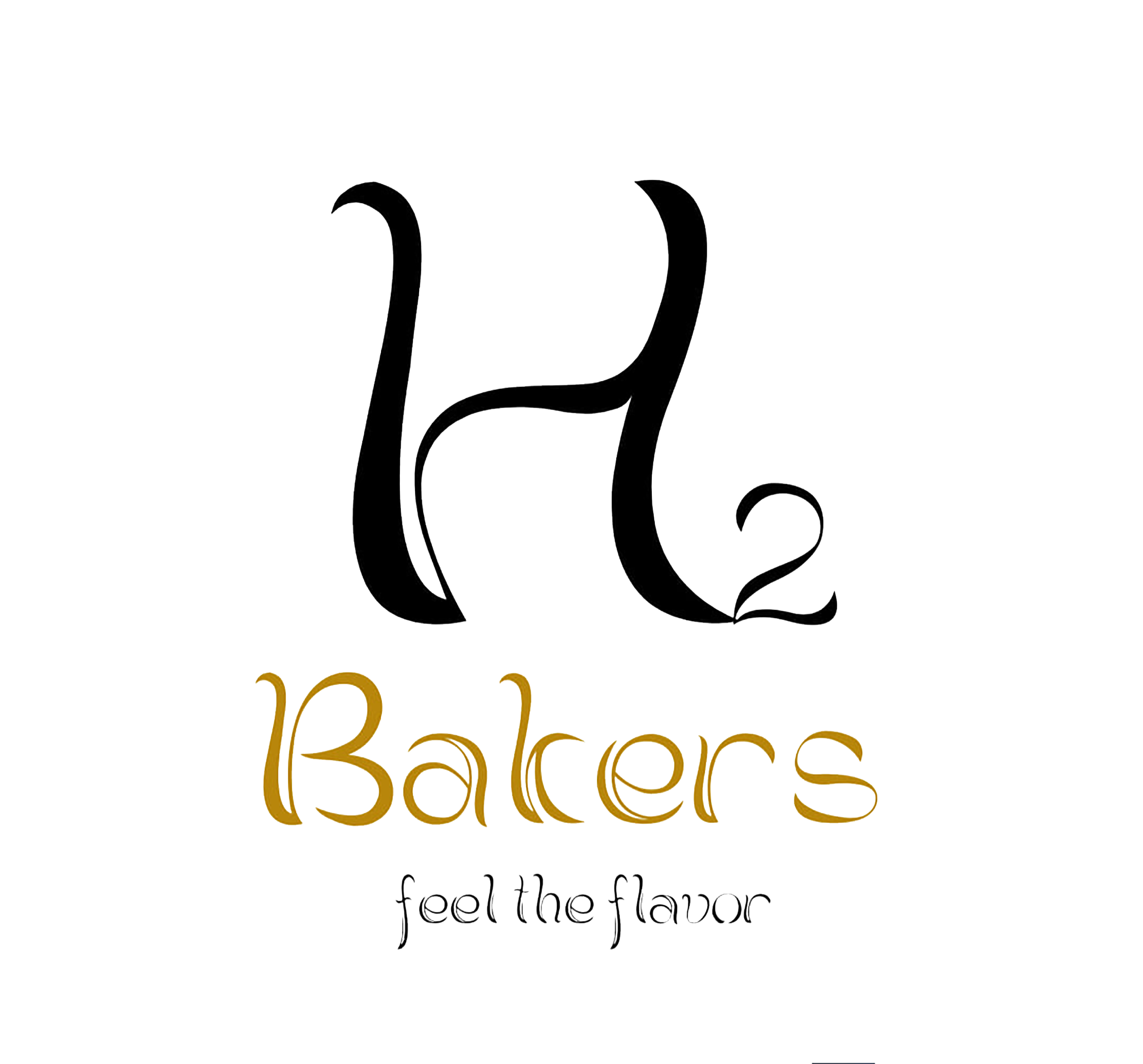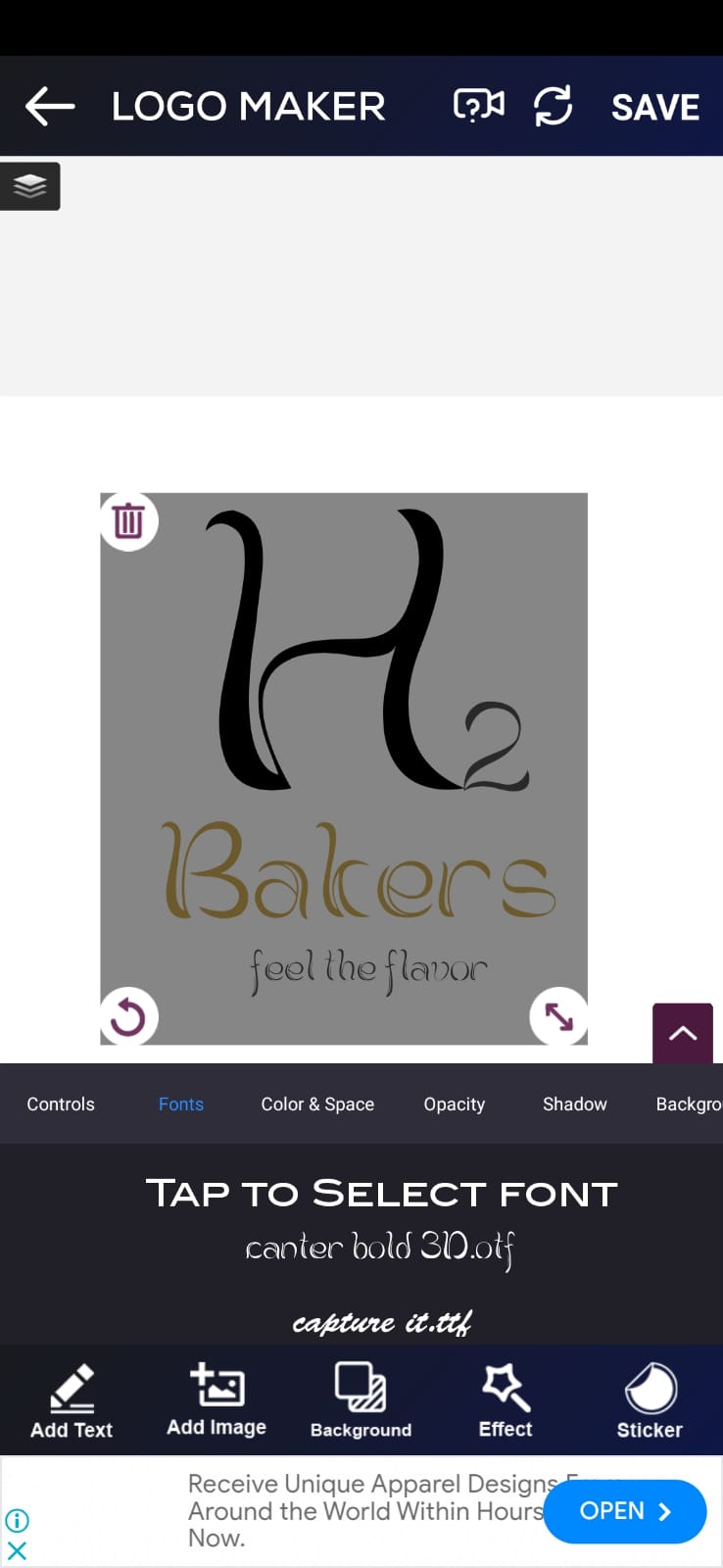
FONT උදව්වක් දන්නා කෙනෙක් කියනවද මේ font එකේ නම පුලුවන්නම් font එක හොයල දෙන්න
chanaka Well-known member May 4, 2006 3,217 781 113 Jun 27, 2024 #1 FONT උදව්වක් දන්නා කෙනෙක් කියනවද මේ font එකේ නම පුලුවන්නම් font එක හොයල දෙන්න
dilann Well-known member Jul 6, 2018 68,605 168,929 113 එකමත් එක රටක Jun 27, 2024 #2 කවුරුහරි එකක් ඇදපු custom font එකක් වගේ .
chanaka Well-known member May 4, 2006 3,217 781 113 Jun 27, 2024 #3 dilann said: කවුරුහරි එකක් ඇදපු custom font එකක් වගේ . Click to expand... නැ බන් logo maker app එහෙක තියන්නේ එකේ නම දාලා තියන්නේ canter bold3D.otf කියල එක දැම්මම වෙන මගුලක් එන්නේ
*danushka* Well-known member Oct 15, 2007 13,922 1,099 113 Hali-ela Jun 27, 2024 #5 https://font.download/font/brahmi Reactions: Thari87, Ysa Karu and Anathai